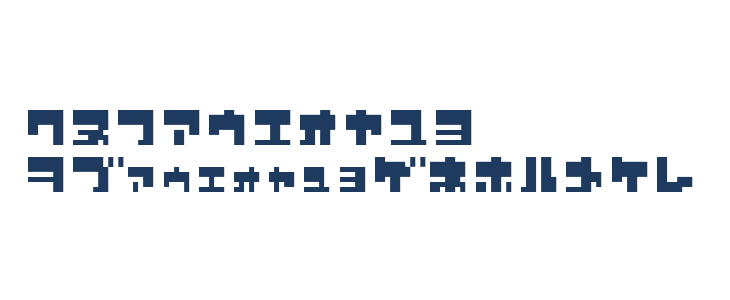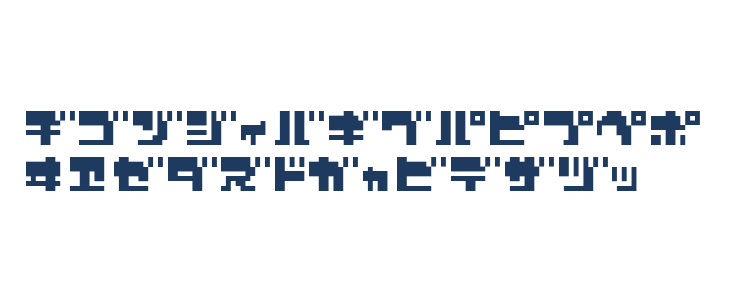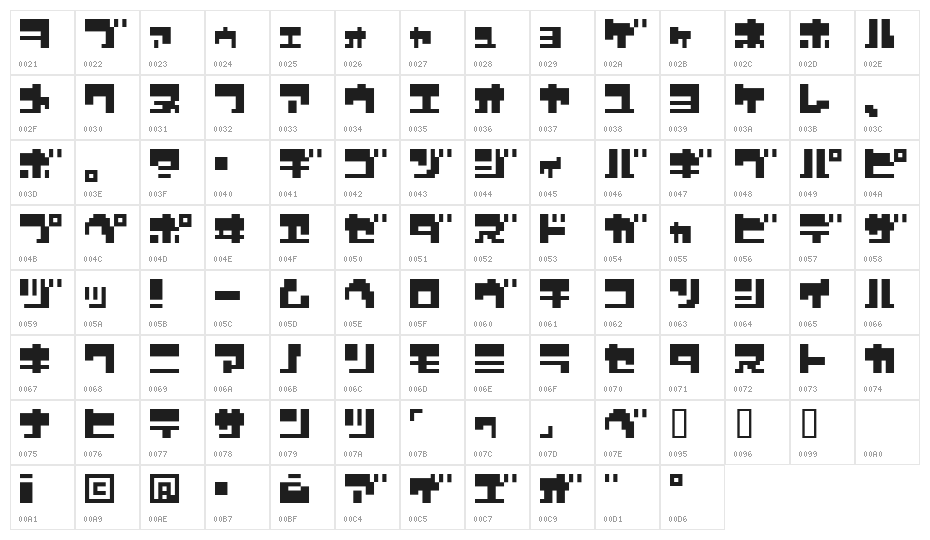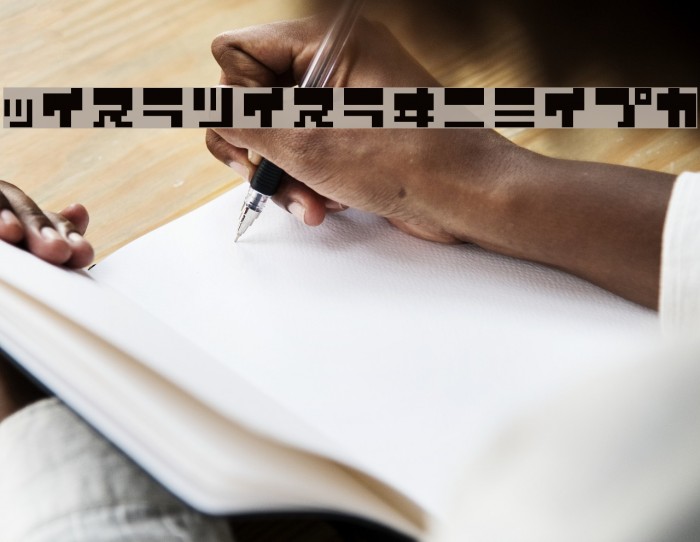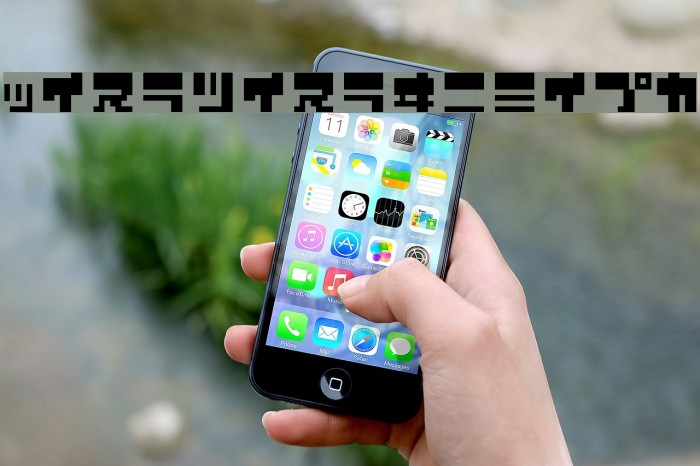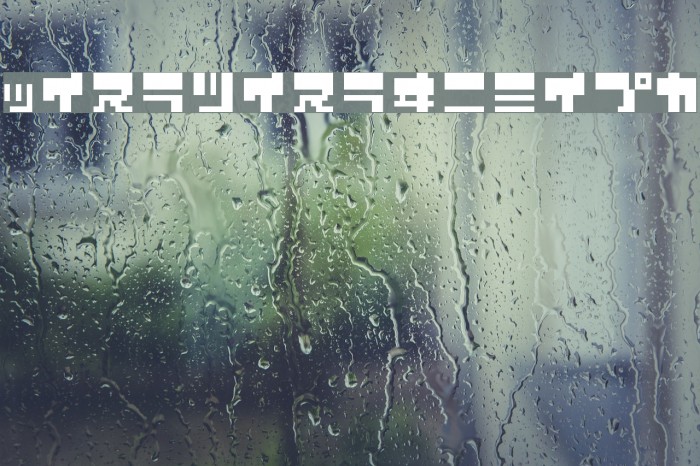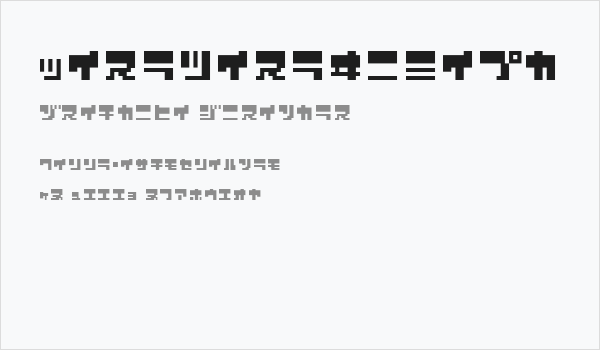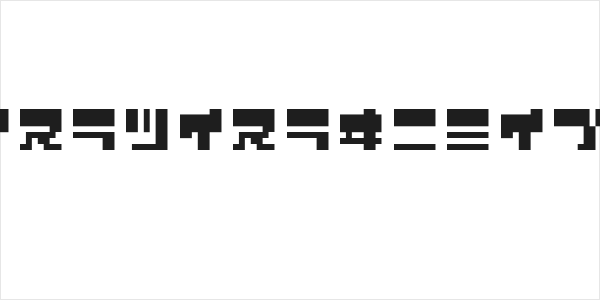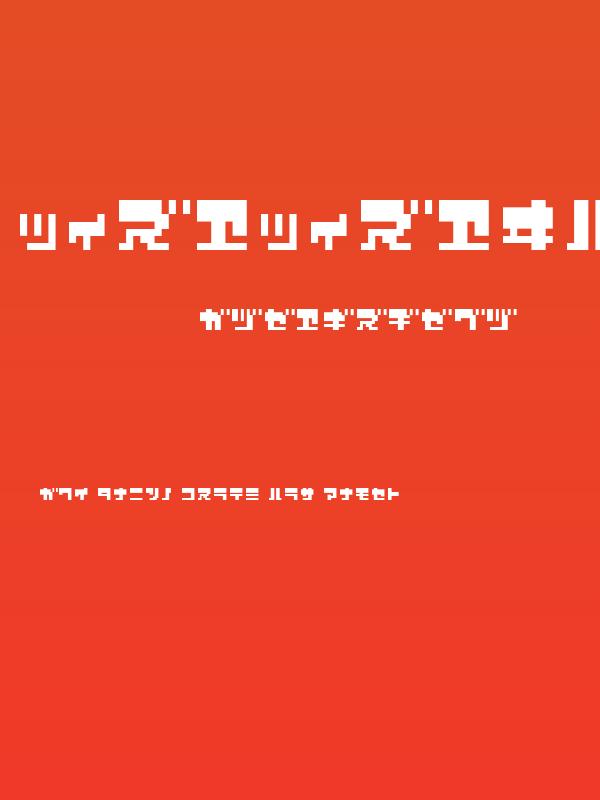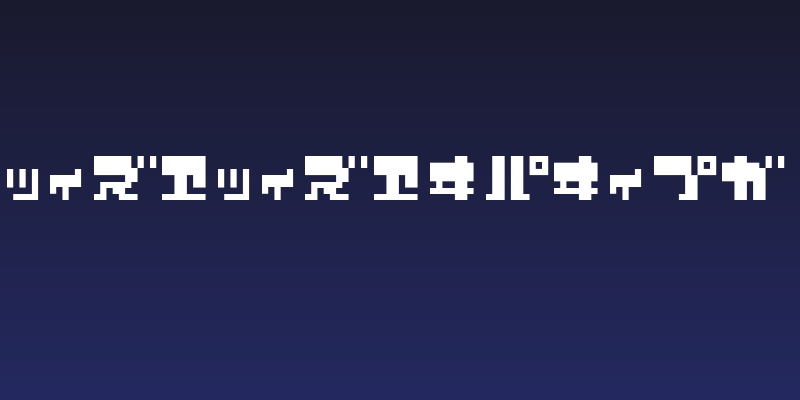
ZerozeroNineKt Font
| Stil general | Retro, Modern |
| Proiecte propuse | Ideal for video game titles, tech-themed posters, digital art projects, and retro-style branding. |